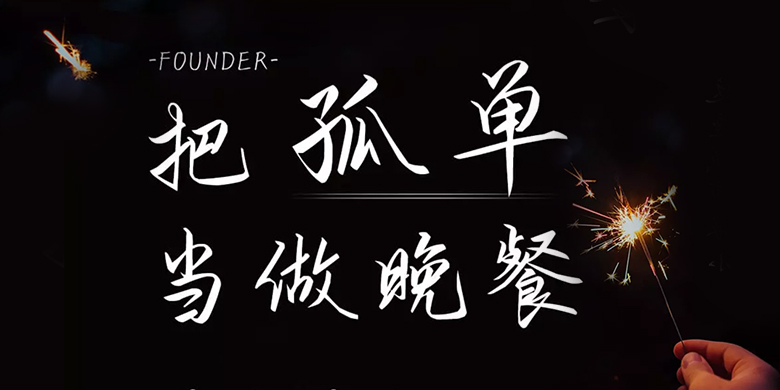
方正手迹-把孤单当做晚餐
字体品牌: 方正手迹 设计师:俞亦婷 字体分类:常规书写·硬笔 字体属性:精品字 字符集:大陆简体(GB2312-80) 发布时间: 2019
把孤单当做晚餐这款字体笔画灵动,字迹潇洒秀气,现代的文艺的气息中又参杂着些许古典书法元素,让人赏心悦目。适用于文艺类的书刊、品牌广告和产品包装设计,以及社交网络的个性化用字。